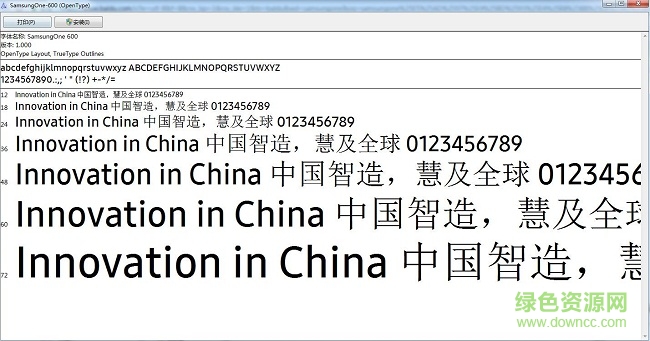
samsungone字體是一款由三星官方推出的一套通用字體,涵蓋字符豐富,大氣美觀,精致耐看,這款字體會出現(xiàn)在三星的各類產(chǎn)品上,需要的朋友快來下載吧!
1.覆蓋了26套書寫系統(tǒng)、400多種語言、25000多個符號
2.SamsungOne的設(shè)計擁有5個核心的原則:人文主義、易區(qū)分、通用、專業(yè)和清晰易讀/可拓展。
3.該字體將有效連接產(chǎn)品/平臺與用戶,三星旗下產(chǎn)品線十分豐富,包括電視、智能手機、微波爐和平板電腦等數(shù)十個產(chǎn)品類別和眾多產(chǎn)品。